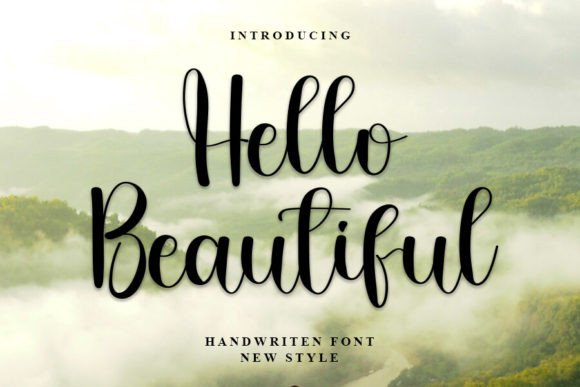
Hello Beautiful
Hello Beautiful – Une police manuscrite qui respire la spontanéité
Hello Beautiful se présente comme une police d’écriture manuscrite fluide, aux strokes organiques et aux courbes douces. Chaque caractère semble tracé à la main, offrant une sensation de chaleur et de convivialité qui capte immédiatement l’attention. Son style naturel et spontané la rend parfaite pour tous les projets où l’on souhaite transmettre une touche d’élégance ludique.
Pourquoi choisir Hello Beautiful ?
- Aspect chaleureux : les traits légèrement irréguliers créent un sentiment d’intimité, idéal pour les invitations de mariage, les cartes de vœux ou les newsletters.
- Versatilité : fonctionne aussi bien pour les citations inspirantes que pour le branding d’emballages de produits artisanaux.
- Lisibilité : malgré son aspect manuscrit, chaque lettre reste claire, ce qui évite les problèmes de lecture sur les supports numériques comme imprimés.
Applications concrètes de Hello Beautiful
Quand on teste Hello Beautiful sur différents supports, le rendu est toujours élégant et plein de charme. Voici quelques exemples d’utilisation qui mettent en valeur son potentiel :
- Invitations de mariage – les lettres cursives ajoutent une note romantique sans paraître trop formelles.
- Affiches de citations – le contraste entre la typographie manuscrite et un fond minimaliste crée un impact visuel puissant.
- Étiquettes de packaging – parfaites pour les produits faits main (bougies, confitures, cosmétiques), elles communiquent authenticité et soin.
- Design de réseaux sociaux – les stories Instagram ou les posts Pinterest gagnent en originalité grâce à cette police.
Conclusion – Hello Beautiful mérite votre attention
En résumé, Hello Beautiful combine spontanéité, chaleur et élégance dans un seul paquet typographique. Que vous soyez graphiste professionnel, créateur de contenu ou simplement à la recherche d’une police qui se démarque, Hello Beautiful est une option fiable qui enrichira vos projets tout en restant facile à lire et à installer.